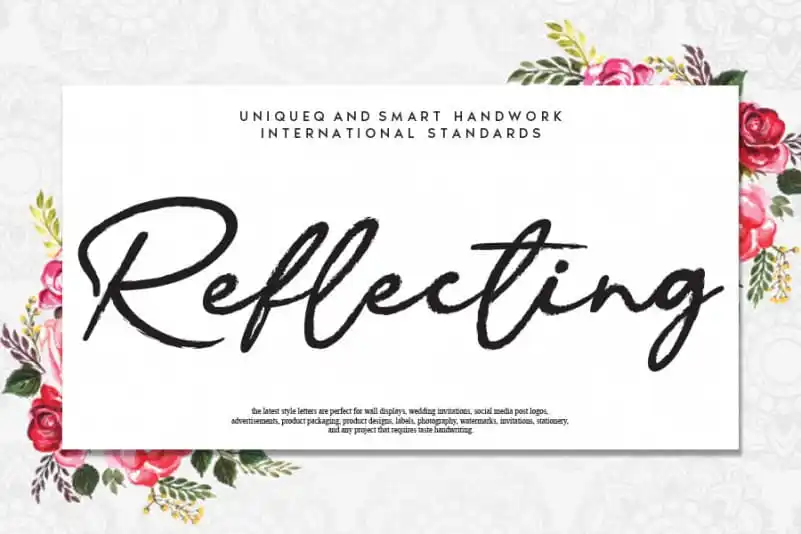
Reflecting Handwritten Font – Download Grátis
Reflecting Handwritten Font é uma elegante tipografia escrita a mão que transmite sofisticação ao mesmo tempo em que mantém uma pegada contemporânea e moderna. Esse recurso de texto, cuidadosamente projetado pelo designer andikastudio, traz um toque especial às suas criações digitais. Apesar do estilo clássico da escrita a mão, sua natureza moderna o torna perfeito para diversos tipos de projetos digitais, desde pequenos anúncios pessoais até layouts complexos de revistas e sites. O que é impressionante é como ele se adapta às diferentes necessidades e estilos sem perder sua beleza singular. Descubra seu potencial para transformar seus trabalhos em algo único e verdadeiramente especial.